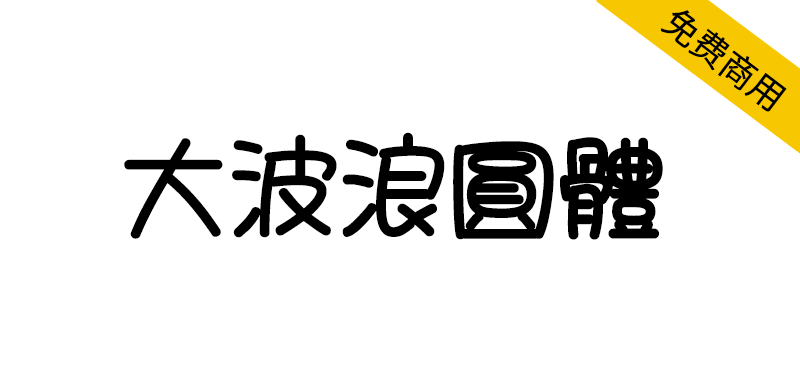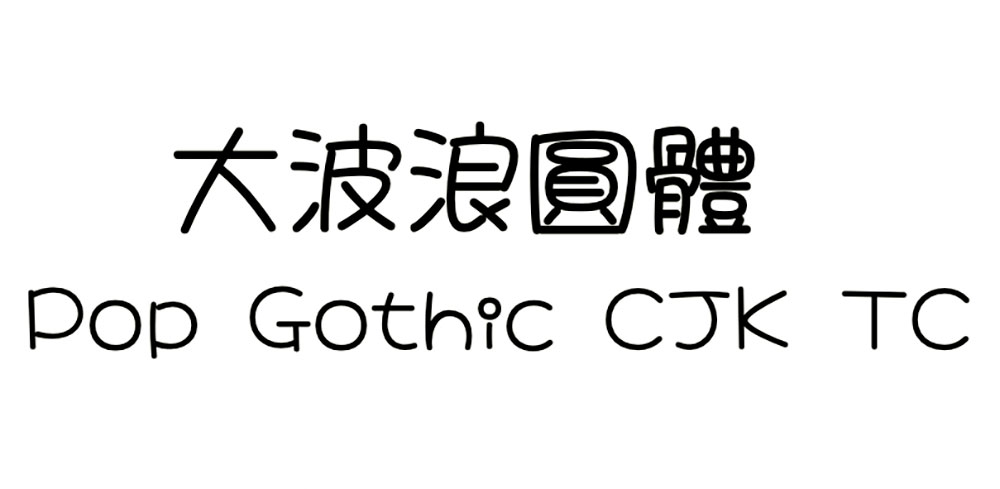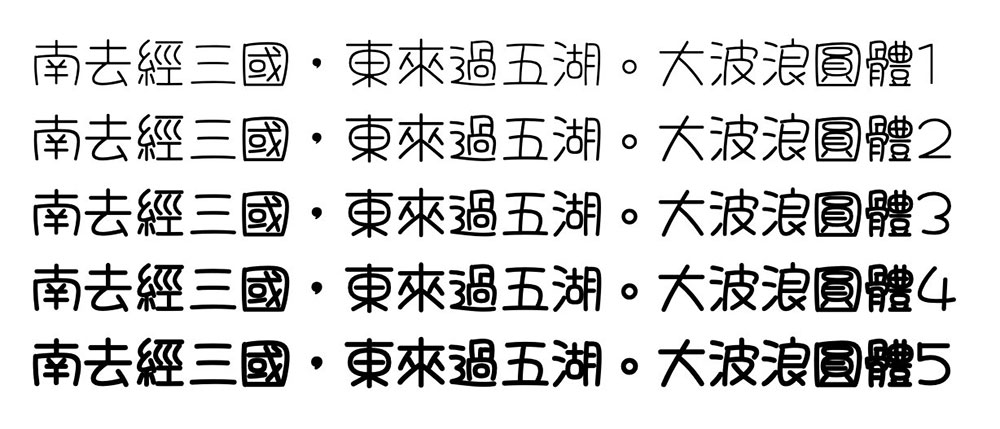
大波浪圆体(Pop Gothic)是 はちまるポップ(Hachi Maru Pop)字体的补字计划。与原作者的主要差异是调整部件写法、新增中文字、增加为5个字重、增加一些符号。可以免费商用,欢迎大家自由应用、自由优化、自由改作!
华康少女字体的风格真的很美,这个项目的目标是取代华康少女体,免费可商业用途的字体,希望大家会喜欢。